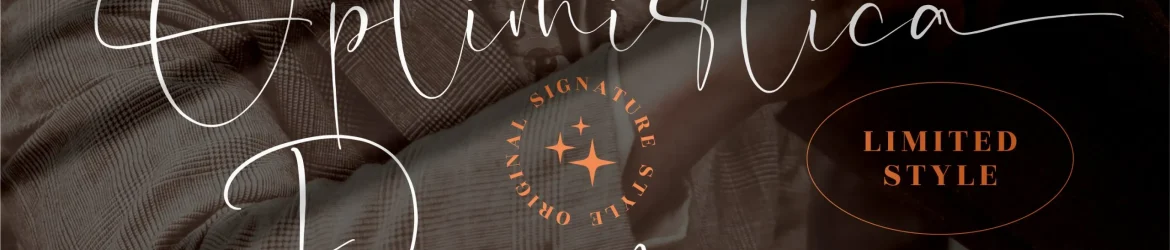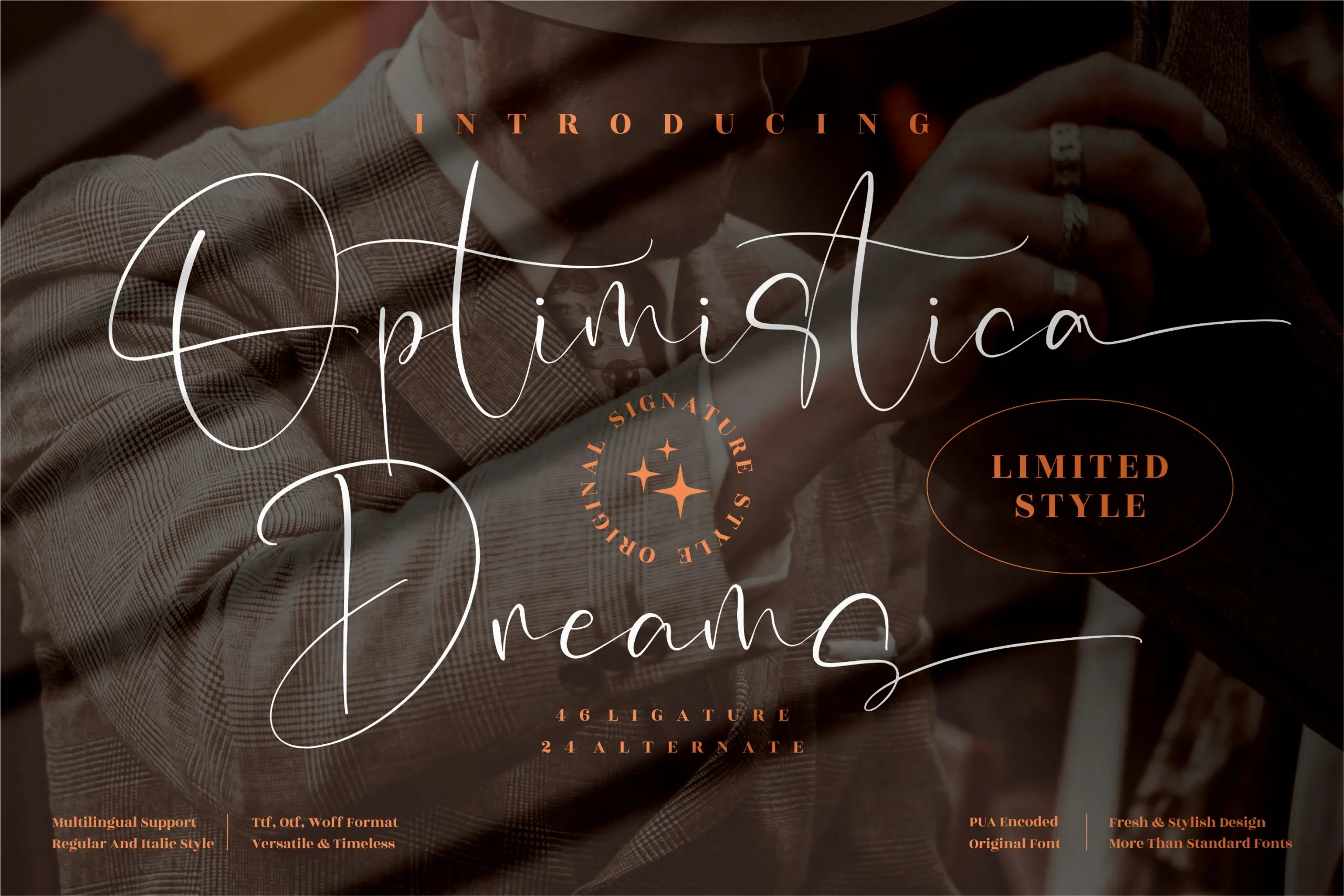
Optimistica Dreams Font – Fonte Grátis
Optimistica Dreams Font
A fonte ‘Optimistica Dreams’ é uma elegante assinatura para qualquer projeto que busque trazer uma sensação fresca ao design. Criada pelo designer perspectype, esta fonte premium é perfeita para a criação de logos, projetos de marca, designs de móveis de casa, embalagens de produtos, tigelas, cartões de post-it, carteiras, convites e cartas de festa, etiquetas, fotos e até mesmo o famoso watermark. Seu moderno estilo assinatura é perfeito para aqueles ambientes que valorizam um toque autêntico, mas com uma aparência contemporânea, tornando-a a escolha ideal para todos os seus projetos de luxo. Seja na criação de um cartão de visita minimalista ou no desenvolvimento de uma identidade visual completa, ‘Optimistica Dreams’ trará profundamente seu toque único e moderno à sua coleção de trabalhos.